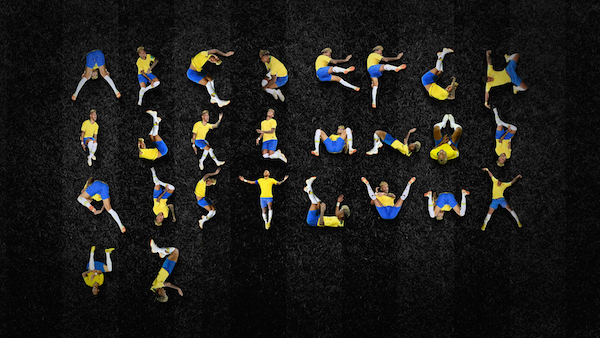
Ney Tipe es una de esas tipografías que sabemos que no utilizaremos pero que nos da gusto que existan; y es que Luciano Jacob, un creativo con sede en Brasil ha demostrado su pasión por el fútbol y su humor por las “actuaciones” de Neymar en el mundial con el diseño de una nueva tipografía inspirada en sus caídas.
Si bien la mayoría del trabajo de Tipos fue hecho por el futbolista; Jacob tuvo que recurrir a la edición para lograr los tipos faltantes por lo que no se trata de una recurso completamente natural.
Tipografía inspirada en Neymar y sus caídas